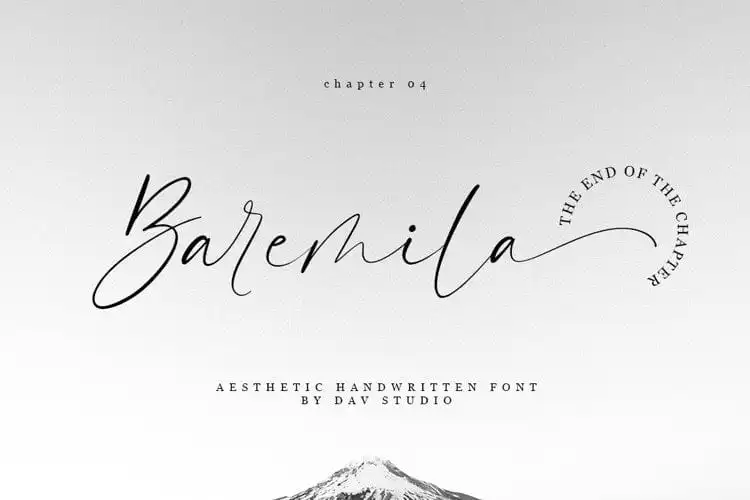
Baremila Script Font – Download Grátis
Baremila Script é uma elegante fonte script que foi criada por Dav Studio para designers buscando um recurso distintivo para seus trabalhos digitais. Com quatro conjuntos de letras, esta fonte possui um toque contemporâneo e sofisticado em cada traço, oferecendo um ar de classe aos designs mais elaborados ou simples que você desenvolver. Os detalhes finos incluem ligaturas e sublinhados nas minúsculas, criando uma sensação suave e encantadora ao redor do seu texto. Baremila Script é perfeito para aqueles desejando dar um toque único e delicado aos seus projetos gráficos, seja em layouts de website, materiais publicitários ou qualquer outro tipo de design digital que deseje expressar uma personalidade única. Com sua textura fluida e sutileza, esta fonte é um excelente complemento para quem procura uma solução criativa e sofisticada.